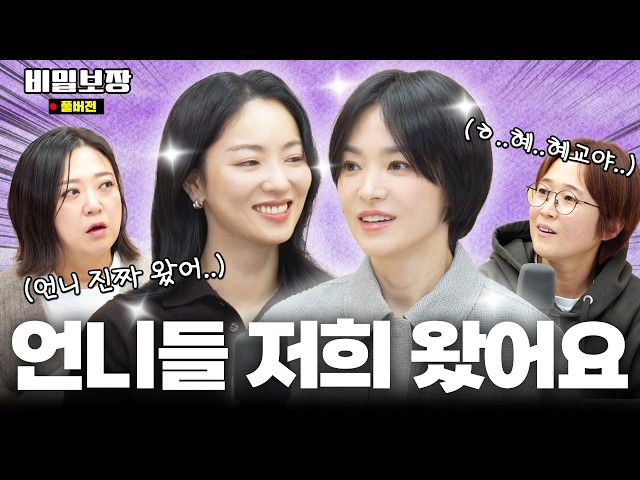
SB어그로체 무료폰트
SB어그로체 — (주)샌드박스네트워크에서 배포하는 무료 폰트입니다. 독특한 곡선과 사선의 조합으로 강한 주목성과 리듬감을 만들어내는 제목용 고딕체
샌드박스네트워크가 만든 첫 브랜드 서체입니다. 출발점이 구체적입니다. 제작사 설명 그대로, 2.5억 명 구독자의 시간을 책임지는 샌드박스 크리에이터와 함께 매달 5천여 개 썸네일 속 콘텐츠에 대한 열정을 바탕으로 만들었다는 것입니다. 유튜브 썸네일에서 시선을 끄는 글자가 그대로 설계 목표가 된 셈이고, 이름의 어그로가 그 기능을 가리킵니다.
제작사가 밝힌 조형은 이렇습니다. 독특한 곡선과 사선의 조합으로 주목도를 높이고, 높이와 폭에서 특유의 리듬감을 느낄 수 있도록 만들었다는 것입니다. 파일에서 재어 보면 자면을 넉넉히 채워 굵고 진한 인상을 냅니다.
굵기는 세 가지입니다. 썸네일과 SNS 카드처럼 눈길을 끌어야 하는 자리에 맞고, 본문이나 중립적인 문서에는 맞지 않습니다. 라이선스는 넉넉한 편이라 개인과 기업 모두 자유롭게 수정하고 변경해 영리·비영리 목적으로 쓸 수 있습니다.